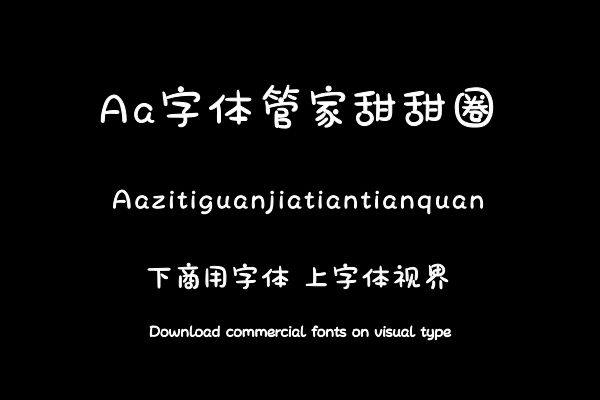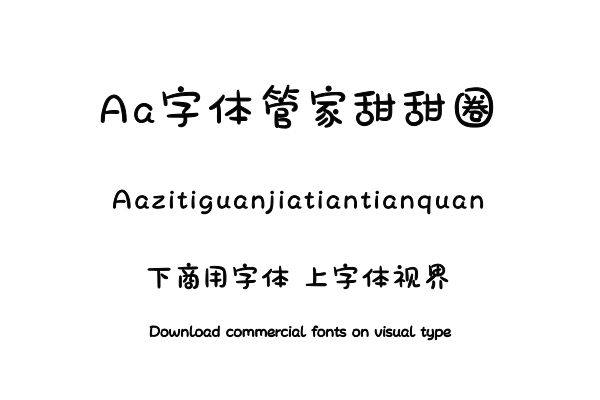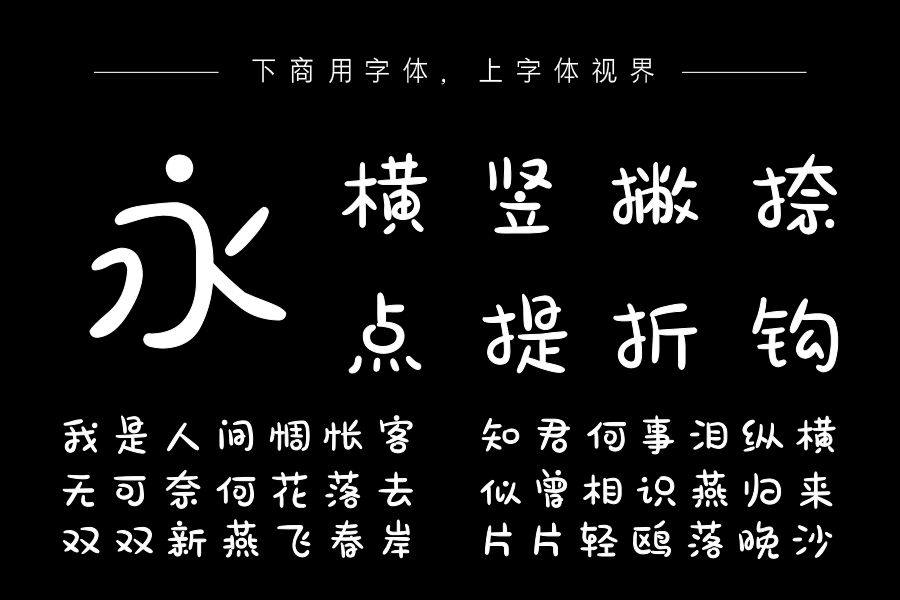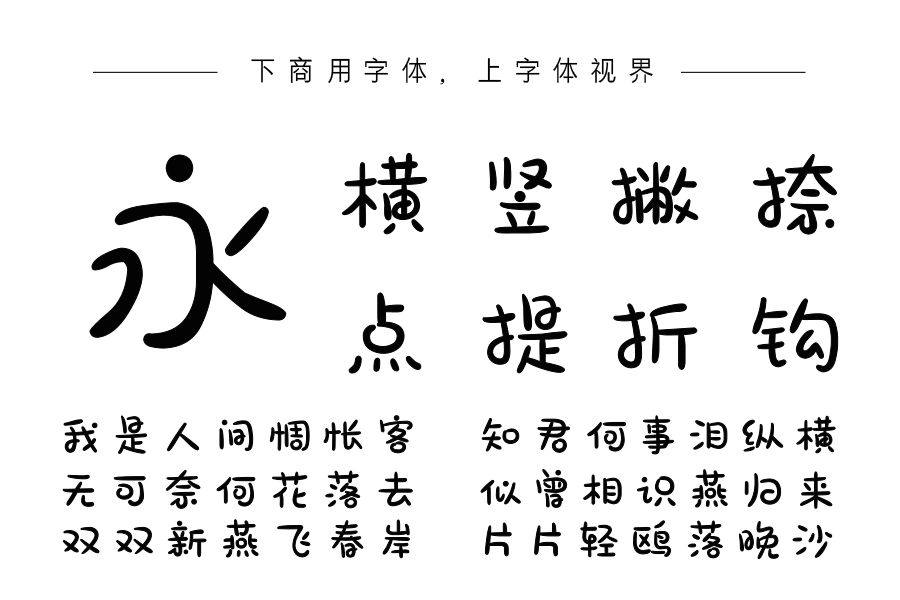
甜甜圈是一款卡通风格的手写体,字形方圆、笔画圆润有弹性、书写灵活。部件大小错落、有节奏,并且相较于普通手写体内白更清晰、笔画光滑,易读性更好。甜甜圈风格独特,作......购买须知:“下载服务费”与“字体VIP”所获得字体 仅用于个人非商用, 商用请联系付费授权。本字体为电脑用字,手机没有root权限不支持直接手机换字(手机如何root,请自行百度搜索教程)。购买前请先 了解清楚后再付款 ,字体为虚拟产品无法回收 一旦购买不支持退款。